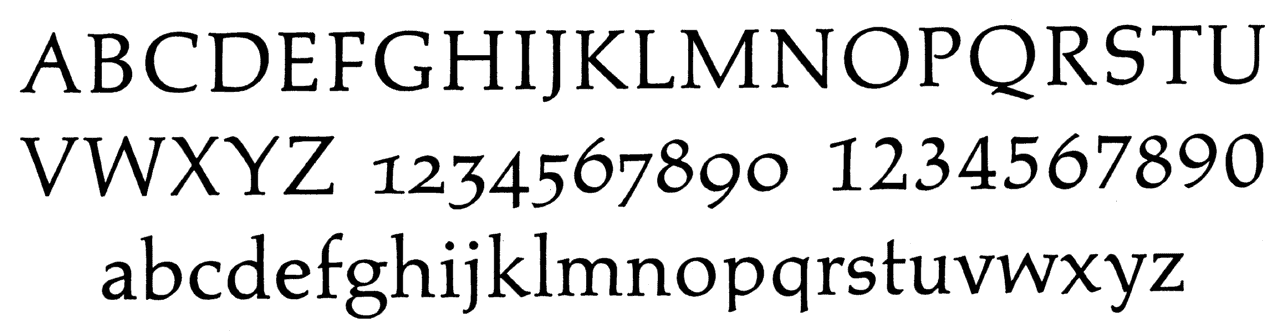
Antiqua unbekannt.
Ganz spontan würde ich eine Palatino vermuten.
Sie hat wirklich sehr viele Ähnlichkeiten mit der Palatino, aber identisch? Schaut euch mal den großen “Wasserkopf” der “9” an:
Die Palatino hatte tatsächlich einmal solche Punzen:
Hallo Bernd, dann wird sie es wohl sein. Zumal der Fuß der “5” leicht nach links gerückt ist, was bei der Palatino auch der Fall ist. Dieses Merkmal ist ziemlich einzigartig.